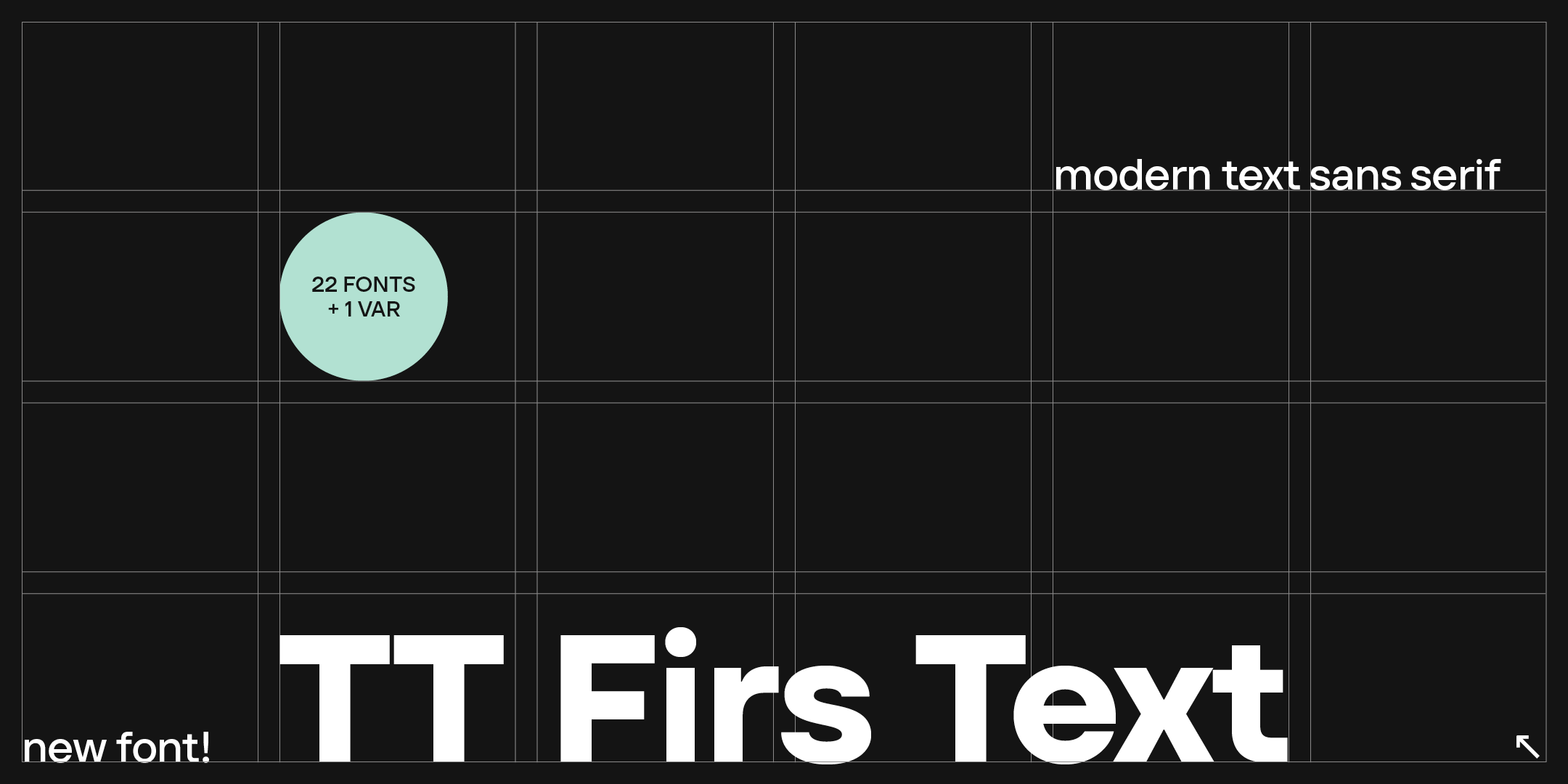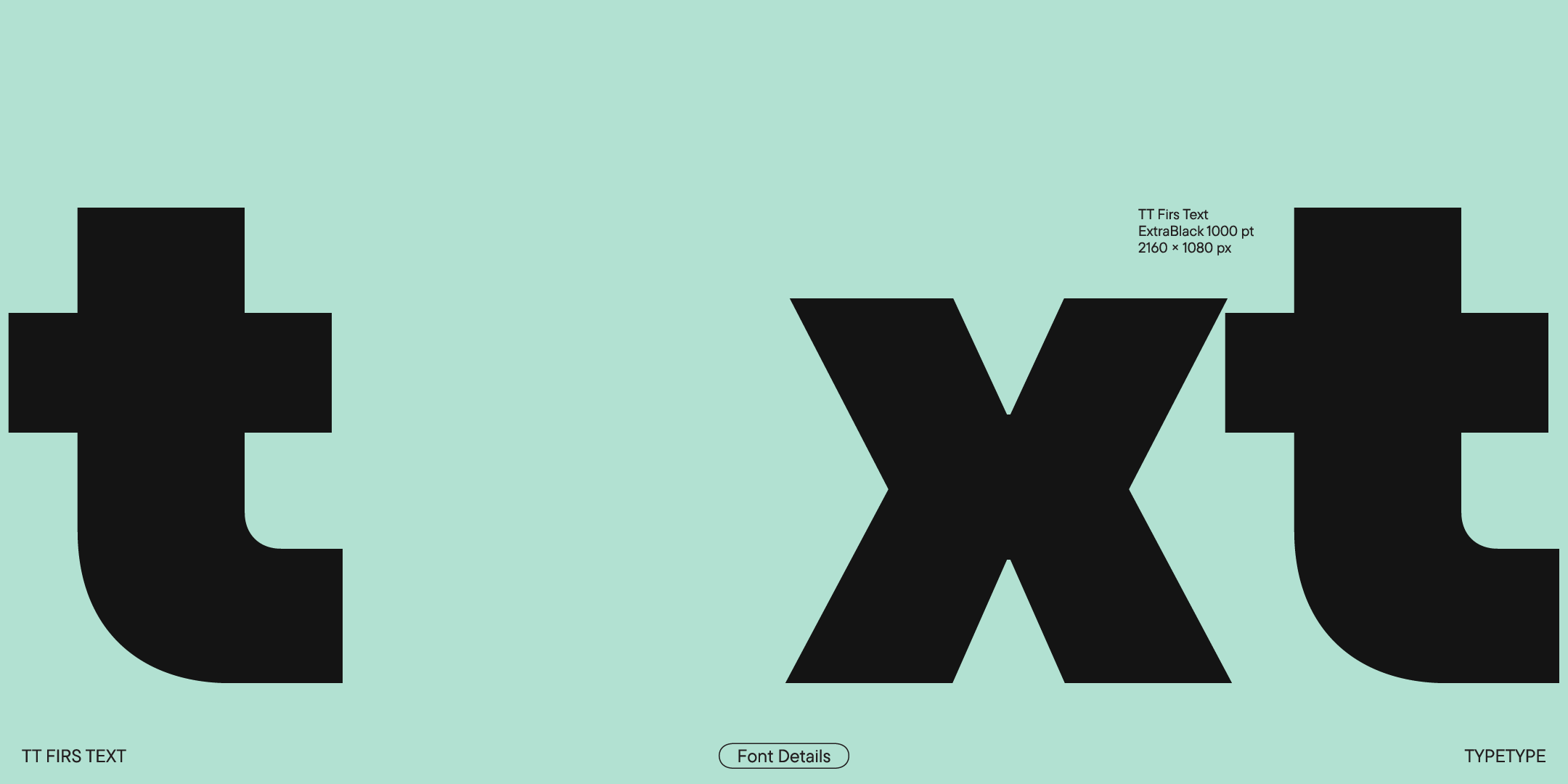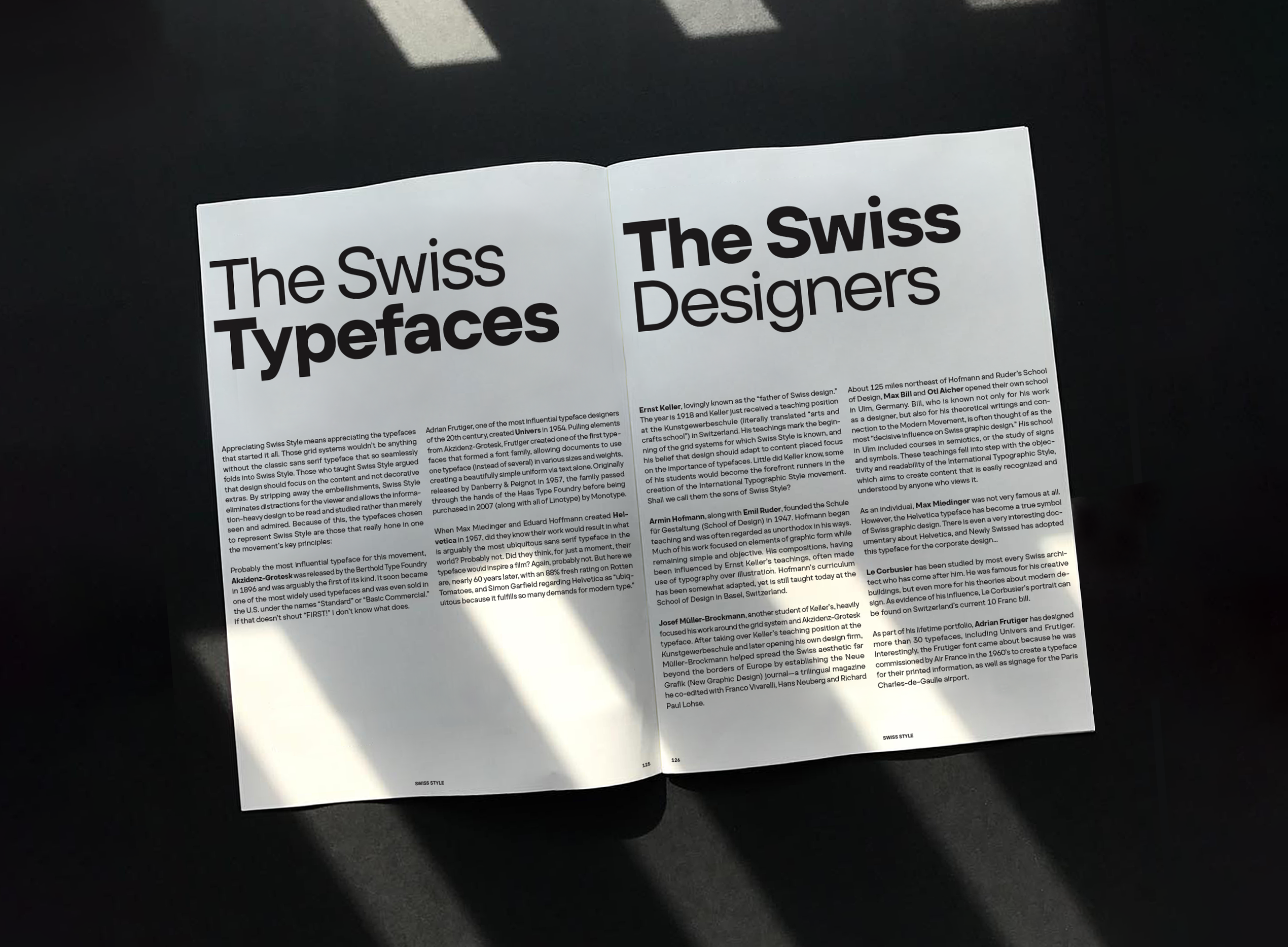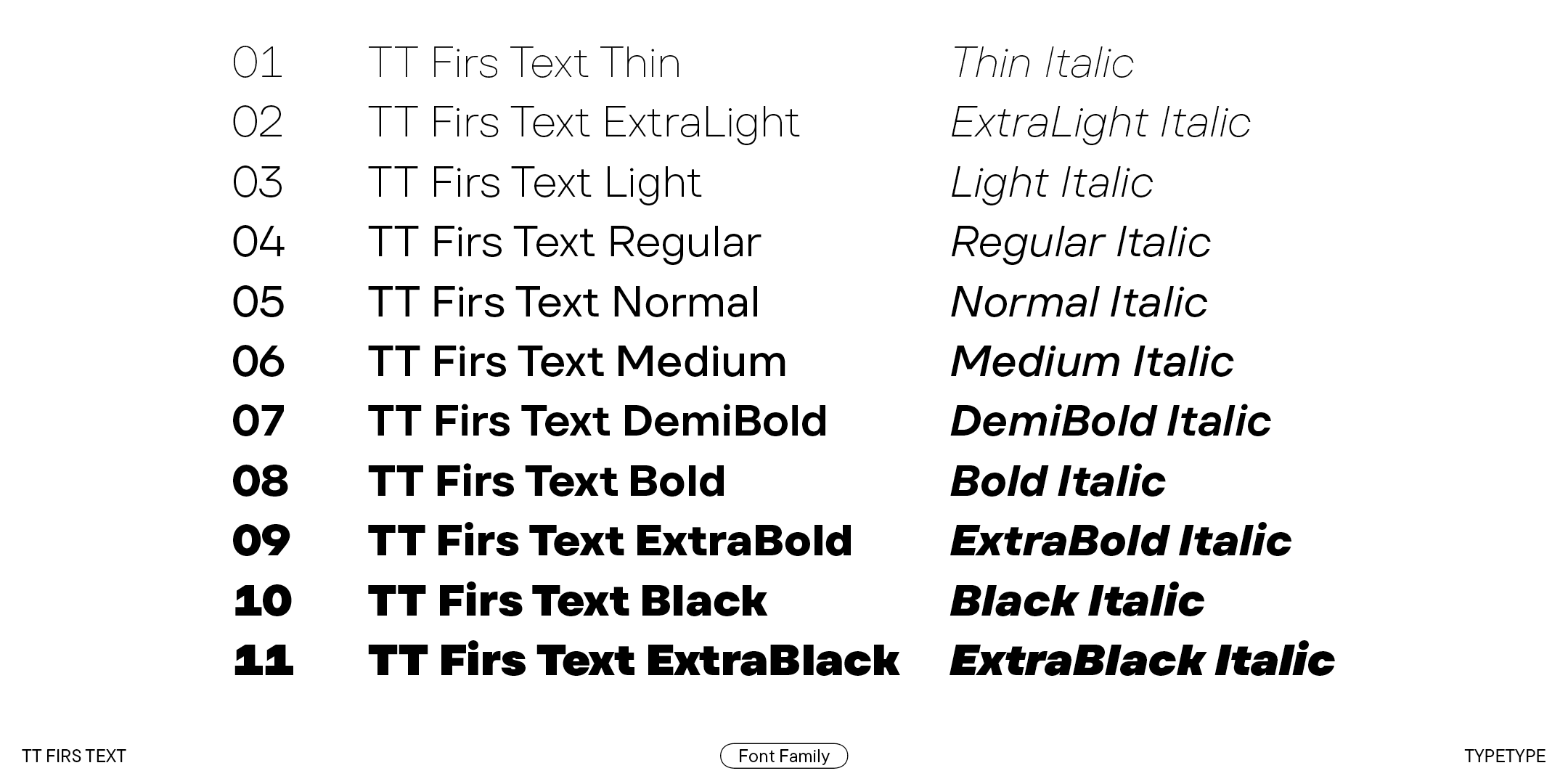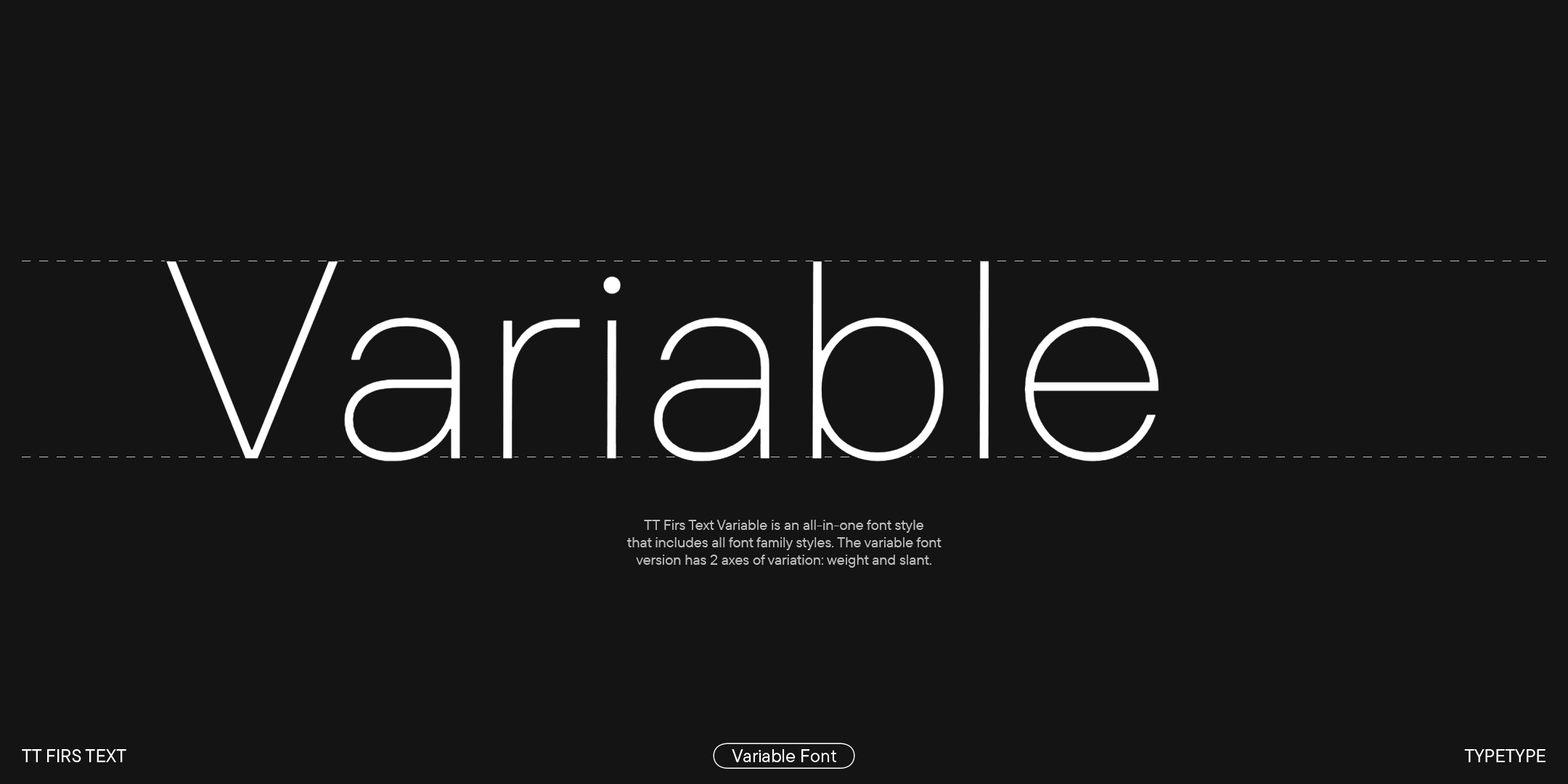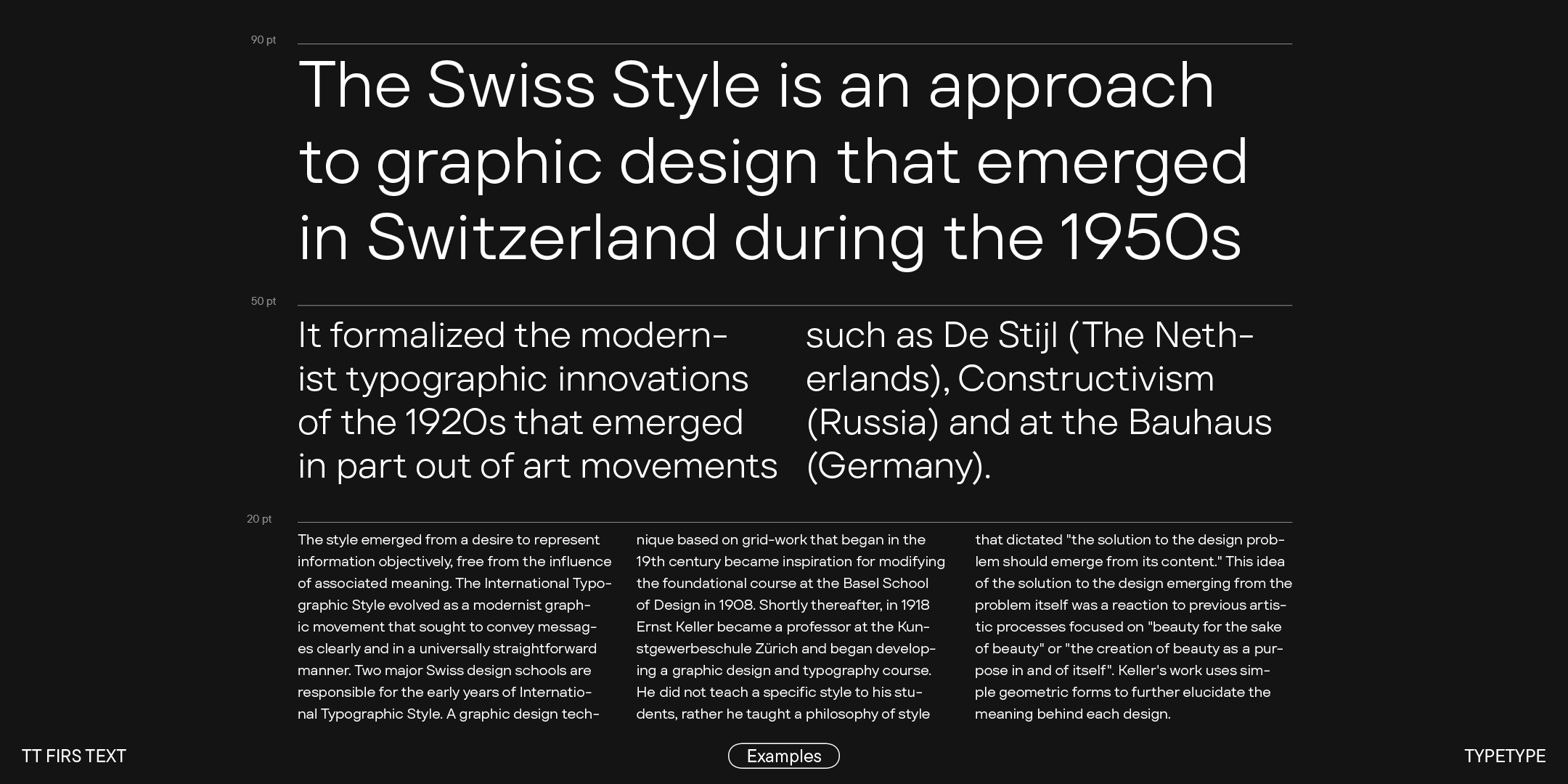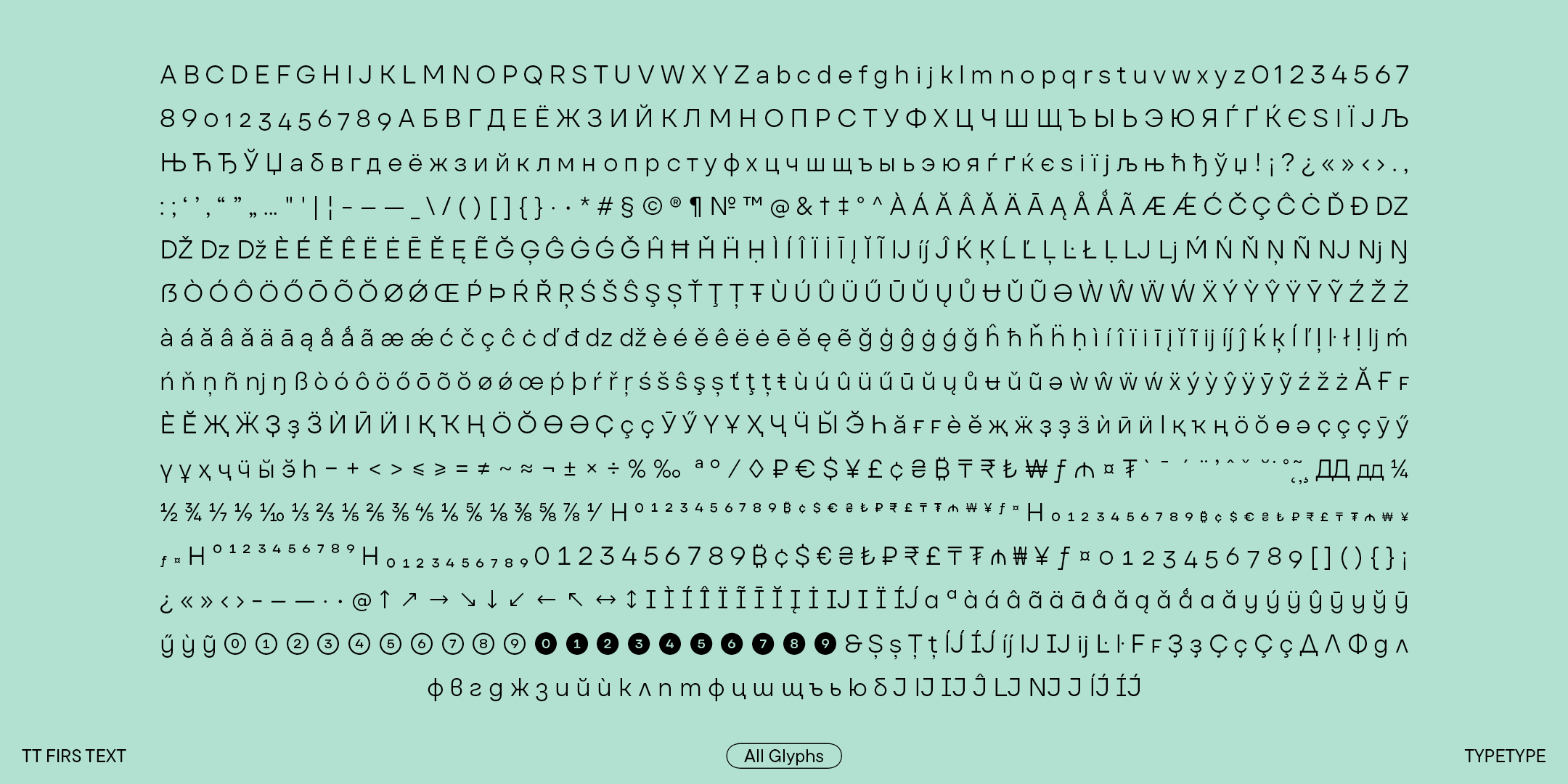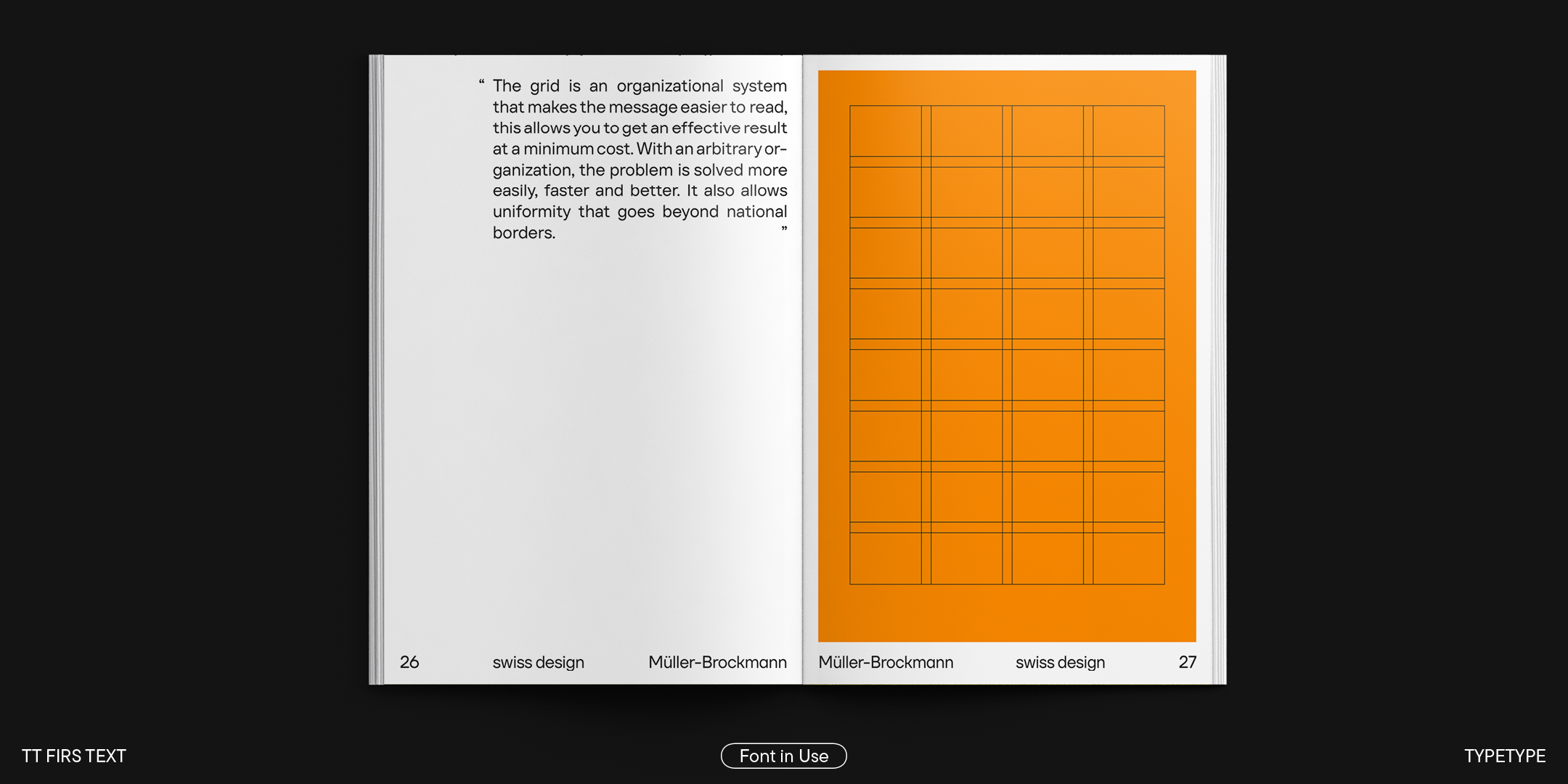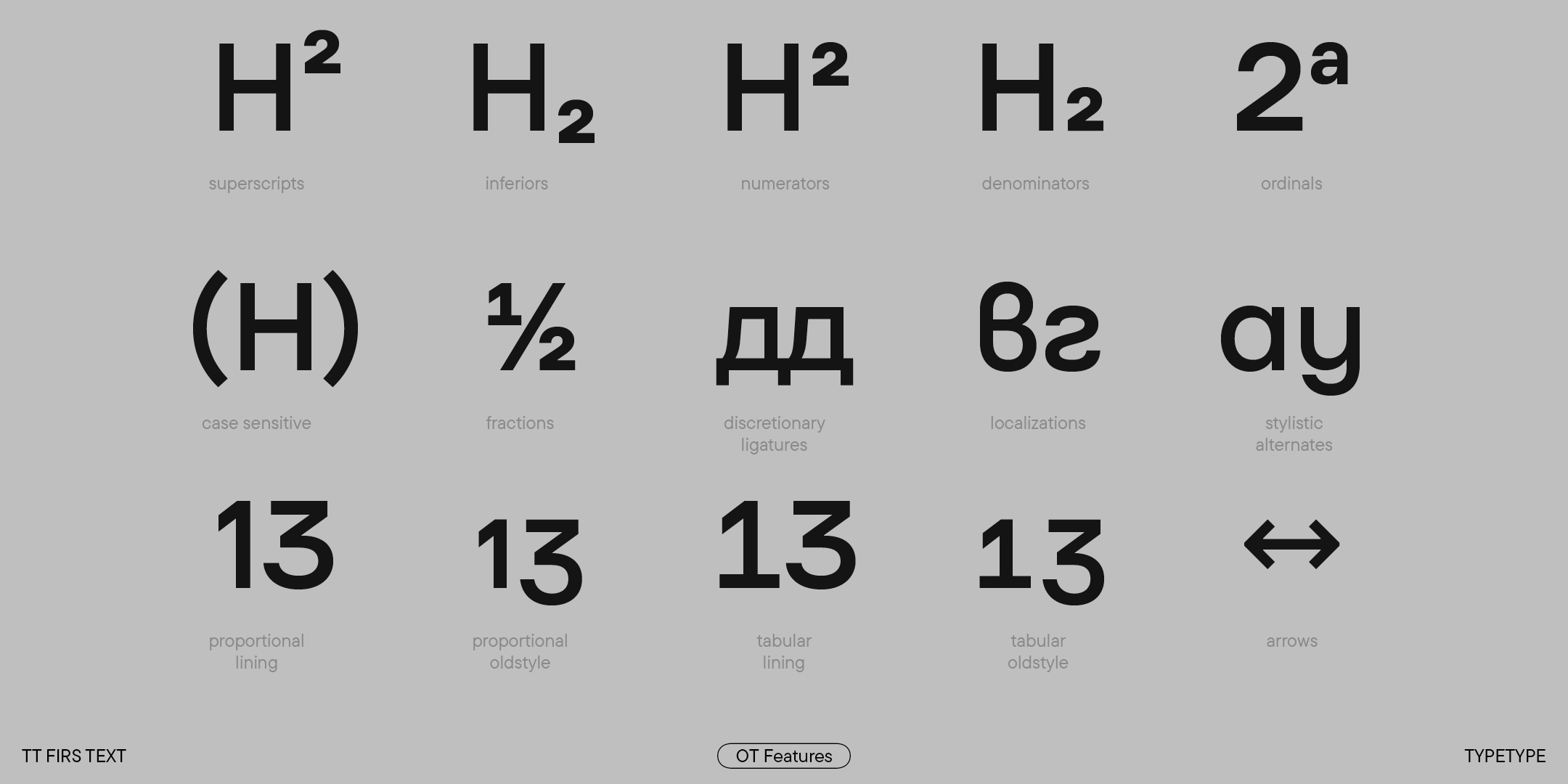
TT Firs Text NEW FONT
Лаконичный геометрический гротеск с нордическим характером: новый шрифт TypeType – TT Firs Text!
TT Firs Text создавался на основе обновленной в 2023 году гарнитуры TT Firs Neue. Мы стремились сделать его еще более нейтральным, но при этом наделить собственным неповторимым стилем.
Мы сохранили эстетику скандинавского минимализма, но полностью перерисовали все выразительные элементы, сделав их более мягкими и традиционными. Набор текста стал более однородным, благодаря чему шрифт остается разборчивым и читаемым даже при наборе массива текста маленьким кеглем.
TT Firs Text получился одновременно холодным и элегантным, строгим и завораживающим, а главное – максимально универсальным. Он одинаково хорошо подойдет для использования на веб-сайтах, книжной верстки, брендинга и дизайна упаковки, оформления плакатов и афиш. Сфера применения практически безгранична.
TT Firs Text состоит из 23 начертаний: 11 прямых, 11 наклонных и 1 вариативного шрифта. В каждом начертании 898 знаков, в том числе знаки расширенной латиницы и кириллицы. Шрифт содержит 31 OpenType фичу, включая фичи локализации для разных языков, нумераторы в кружках и стилистическую альтернативу для амперсанда.